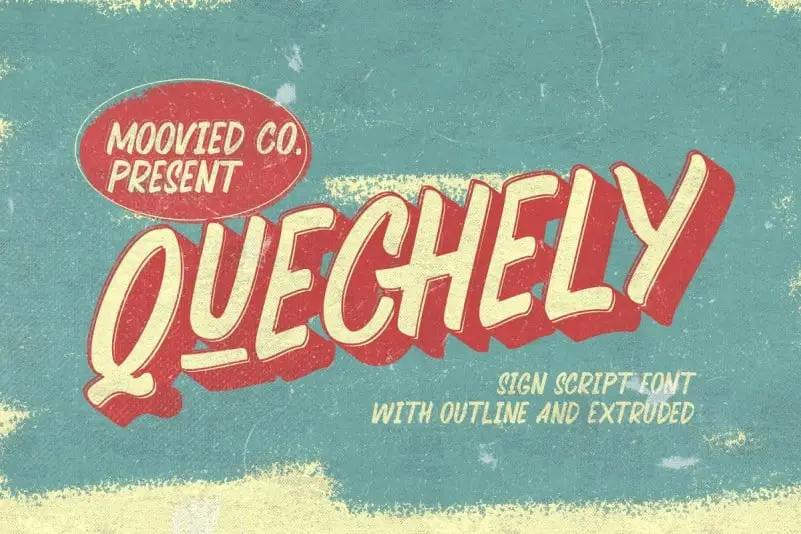
Quechely Sign Retro Font – Download Grátis
A Quechely Sign Retro Font é uma nova adição para a categoria de fonts de script, inspirada em logotipos de letra caída e fontes retro dos anos 60. Esta font foi projetada pela Moovied Co., oferecendo um novo nível de personalização para os anúncios que buscam um design vintage. Essa font vem com três estilos: linhas, sombras e uma combinação de ambos. Ela traz vida ao conceito de letras caídas retro, mantendo os elementos do design daquele período, oferecendo designers a oportunidade de adicionar personalidade aos seus projetos sem se perder no desconhecido. Ideal para criar anúncios que remetem à era dos anos 60, esta font vem com uma versão bold que permite texturas suaves e estilos mais modernos ao mesmo tempo. A Quechely Sign Retro Font é perfeita para quem busca dar um toque nostálgico em suas criações digitais, seja através de anúncios impressos ou conteúdo online. Seja você um designer gráfico aficionado ou profissional, esta font adiciona uma pegada inovadora ao seu trabalho. A Moovied Co. compartilha mais recursos como este para ajudar os designers a explorarem as possibilidades do design e da arte digital.